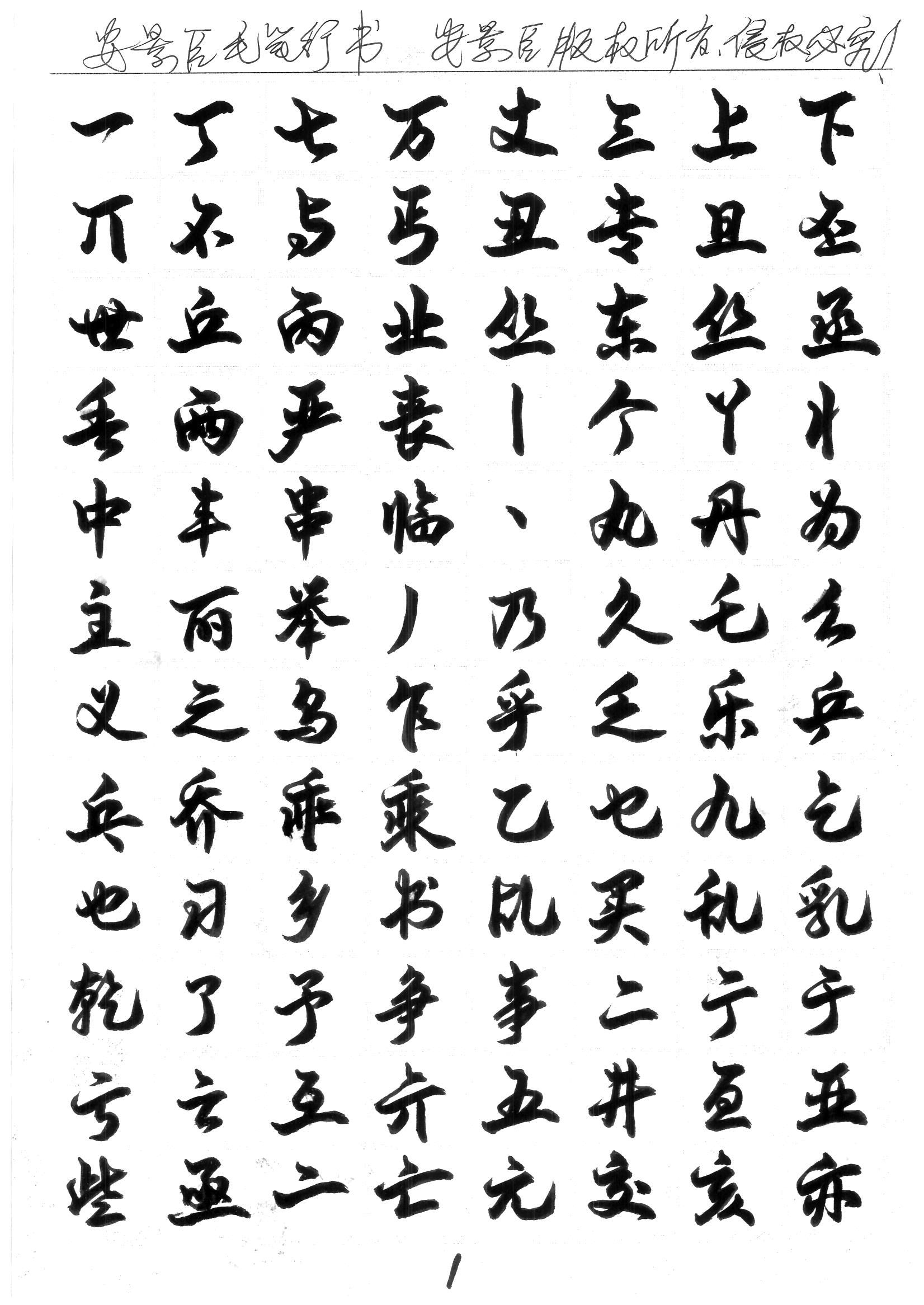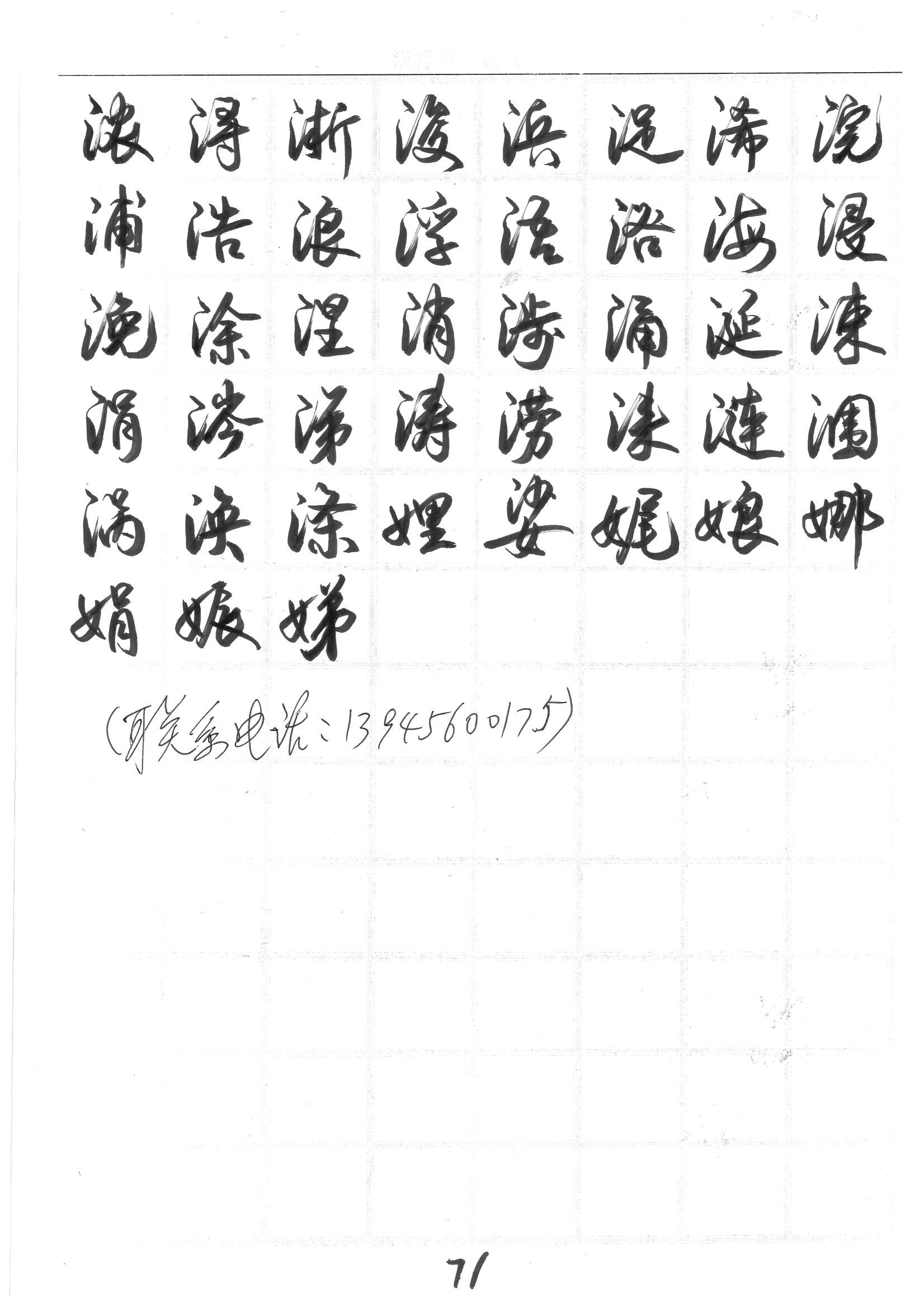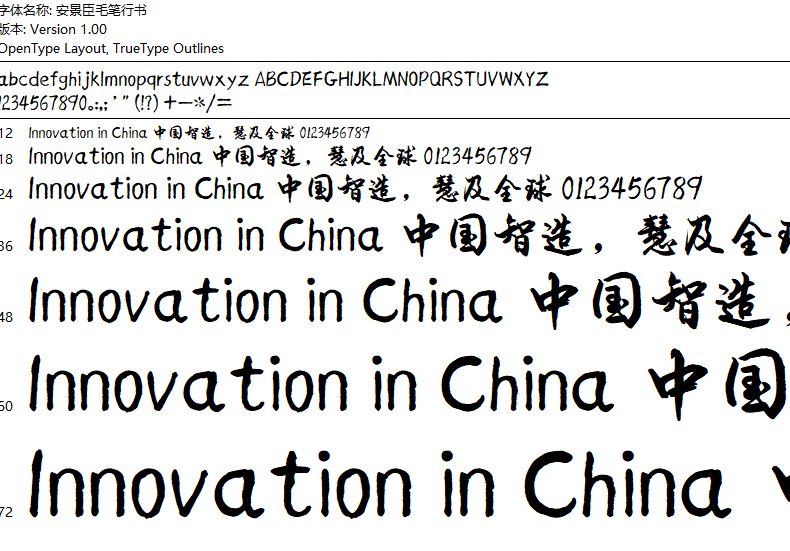
安景臣毛笔行书字体字库
读书破万卷,下笔如有神。
风格:美术字体
语系:中文-简体
字数:GB2312(6763字)
类型:行书
读书破万卷,下笔如有神。
描述:一款规范且灵动的毛笔行书字体,广泛应用于影视字幕标题、商标标志设计、企业名称、产品名称等。采用现代特制毛笔,时代感强且高雅脱俗。
安景臣字体